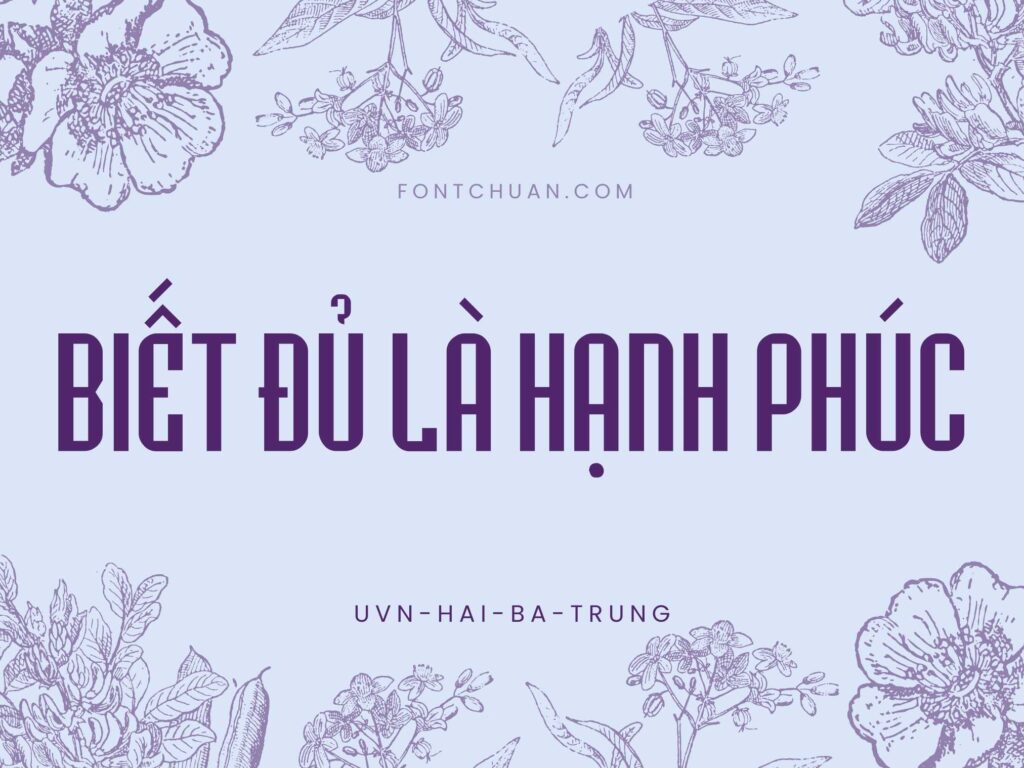
Font UVN Hai Ba Trung Việt Hóa
UVN Hai Ba Trung là một phông chữ sans-serif mang phong cách hiện đại, được thiết kế bởi Tom Truong vào năm 2001. Phông chữ này có các đường nét rõ ràng và tinh tế, tạo nên sự thanh lịch và dễ đọc. UVN Hai Ba Trung hỗ trợ đầy đủ các ký tự tiếng Việt, giúp người dùng dễ dàng sử dụng trong các dự án liên quan đến ngôn ngữ Việt Nam.
Với thiết kế hiện đại và rõ ràng, UVN Hai Ba Trung phù hợp cho các ứng dụng như tiêu đề, văn bản, thiết kế logo và các ấn phẩm truyền thông. Trong lĩnh vực sự kiện, phông chữ này có thể được sử dụng trong các dịp như hội thảo, triển lãm và các sự kiện doanh nghiệp. Ngoài ra, UVN Hai Ba Trung cũng thích hợp cho các ngành nghề như thiết kế đồ họa, truyền thông và giáo dục.